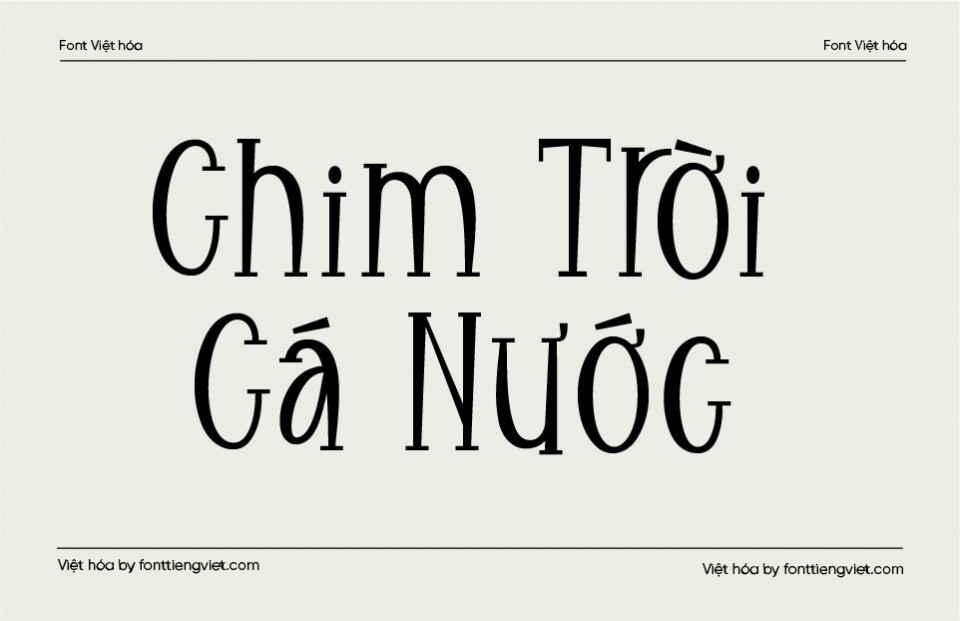
Font Việt hóa 1FTV VIP Eitaro – Bộ font chữ sáng tạo cho thiết kế hiện đại Giới thiệu về Font Việt hóa 1FTV VIP Eitaro và xu hướng thiết kế Trong thế giới sáng tạo đồ họa ngày nay, việc lựa chọn một bộ Font Miễn Phí chất lượng luôn là ưu tiên hàng đầu của các nhà thiết kế chuyên nghiệp cũng như các bạn học sinh sinh viên. Font Việt hóa 1FTV VIP Eitaro nổi lên như một hiện tượng nhờ sự kết hợp hoàn mỹ giữa nét vẽ tay mộc mạc và cấu trúc hiện đại. Đây là bộ font chữ mang phong cách tối giản nhưng không kém phần tinh tế, giúp các tác phẩm thiết kế trở nên nổi bật và có chiều sâu hơn. Việc sử dụng Font Việt hóa 1FTV VIP Eitaro không chỉ giúp giải quyết bài toán hiển thị tiếng Việt mà còn mang lại cảm giác gần gũi, thân thiện cho người xem qua từng nét chữ thanh thoát. Những đặc điểm nổi bật của Font Việt hóa 1FTV VIP Eitaro Thiết kế độc đáo và tính ứng dụng cao Điểm mạnh nhất của Font Việt hóa 1FTV VIP Eitaro chính là hệ thống ký tự được chăm chút kỹ lưỡng, đảm bảo tính cân đối trên mọi phương diện. Các dấu câu trong tiếng Việt được đặt đúng vị trí, không bị lệch hay chồng chéo lên nhau, điều mà nhiều bộ font quốc tế thường gặp phải khi chưa được Việt hóa chuẩn. Font Việt hóa 1FTV VIP Eitaro phù hợp cho nhiều mục đích khác nhau từ làm thiệp chúc mừng, thiết kế bìa sách, poster quảng cáo cho đến các bài thuyết trình trên lớp. Sự linh hoạt này giúp người dùng tiết kiệm thời gian đáng kể trong việc tìm kiếm font chữ phù hợp cho từng dự án cụ thể. Khả năng tương thích trên nhiều nền tảng Bên cạnh yếu tố thẩm mỹ, Font Việt hóa 1FTV VIP Eitaro còn ghi điểm bởi khả năng hoạt động mượt mà trên nhiều phần mềm thiết kế phổ biến như Adobe Photoshop, Illustrator, Canva hay thậm chí là các ứng dụng văn phòng cơ bản như Microsoft Word và PowerPoint. Người dùng hoàn toàn có thể yên tâm rằng Font Việt hóa 1FTV VIP Eitaro sẽ giữ nguyên được hình dáng ban đầu mà không bị lỗi hiển thị khi chuyển đổi file giữa các thiết bị khác nhau. Điều này đặc biệt hữu ích cho các bạn học sinh cần trình bày tiểu luận hoặc làm bài tập nhóm một cách chuyên nghiệp nhất. Cách tối ưu hóa Font Việt hóa 1FTV VIP Eitaro trong trình bày Phối hợp màu sắc và bố cục Để Font Việt hóa 1FTV VIP Eitaro phát huy tối đa vẻ đẹp, bạn nên kết hợp với những tông màu trung tính hoặc pastel nhẹ nhàng. Việc sử dụng khoảng cách dòng và khoảng cách chữ hợp lý sẽ giúp nội dung trở nên dễ đọc và bắt mắt hơn. Đừng ngần ngại sử dụng định dạng strong hoặc em để nhấn mạnh những thông điệp quan trọng trong đoạn văn. Một bố cục thoáng đãng cùng với sự hiện diện của Font Việt hóa 1FTV VIP Eitaro chắc chắn sẽ để lại ấn tượng mạnh mẽ cho thầy cô và bạn bè khi xem sản phẩm của bạn. Kết luận về giá trị của Font Việt hóa 1FTV VIP Eitaro Tổng kết lại, Font Việt hóa 1FTV VIP Eitaro là một công cụ hỗ trợ đắc lực không thể thiếu trong kho tài nguyên của bất kỳ ai yêu thích cái đẹp và sự chỉn chu. Với việc cung cấp hoàn toàn miễn phí, bộ font này đã mở ra cơ hội tiếp cận nghệ thuật chữ viết chuyên nghiệp cho tất cả mọi người. Nếu bạn đang tìm kiếm một giải pháp để nâng tầm các dự án cá nhân, hãy trải nghiệm ngay Font Miễn Phí, Font Việt Hóa, Font Việt hóa 1FTV VIP Eitaro để cảm nhận sự khác biệt vượt trội trong từng đường nét. Chúc các bạn có những trải nghiệm thiết kế tuyệt vời và đầy cảm hứng với bộ chữ đặc sắc này.
Font Việt hóa 1FTV VIP Eitaro